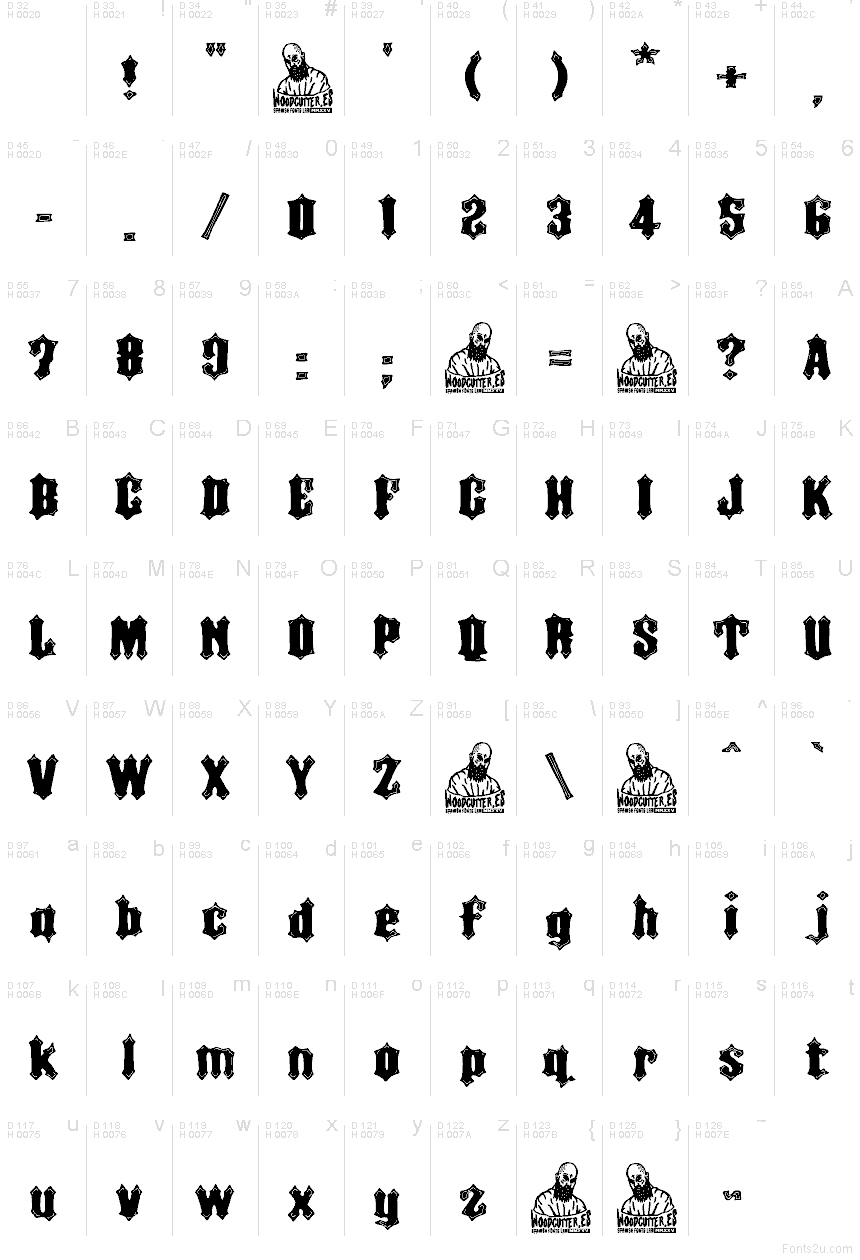
Hierro Templado
Hierro Templado von Woodcutter Manero ist eine kostenlose gotische Display-Schrift. Ihre gemeißelten Blackletter-Formen, Spitzbögen und Kerbdetails verleihen den Buchstaben eine formelle, beinahe mittelalterliche Note. Die Striche wirken eher geformt als gezeichnet; kleine Kerben und scharfe Winkel ziehen sich durch die gesamte Familie und erzeugen einen dichten, ornamentalen Rhythmus.
Hierro Templado eignet sich hervorragend für Logos, Albumcover, Spielmenüs, Veranstaltungsflyer und Titel, bei denen eine gotische Struktur das Design tragen soll. Diese kostenlose Schrift passt zudem perfekt zu Tattoo-Designs, Merchandising und dekorativen Etiketten, da ihre scharfen Formen als starkes Akzent-Element ohne zusätzliche Verzierungen auskommen.